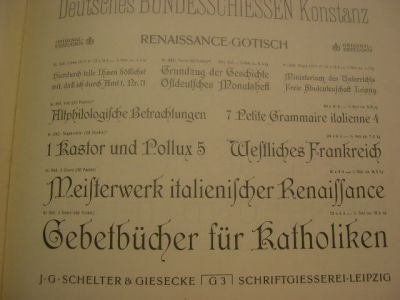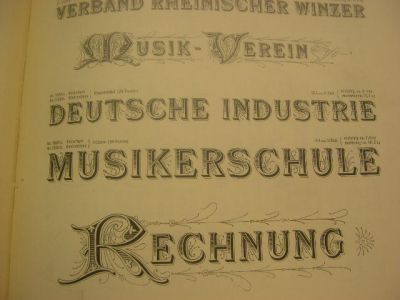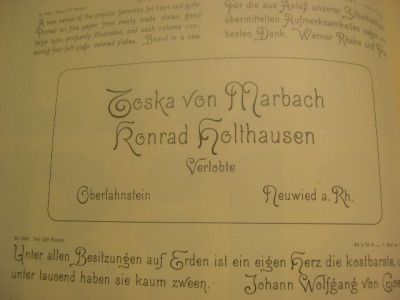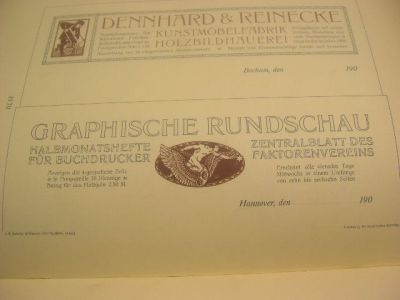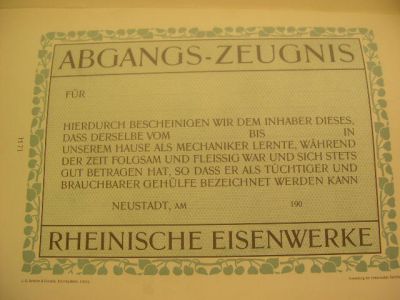
Gott grüß die Kunst.
Das möchte ich als Bleisetzer Euch digitalen Typographen zurufen und damit auch gleich feststellen, daß ich, als Mann der Bleisatz-Zeit, Eure Arbeit durchaus schätze. Darüber hinaus sehe ich sinnvolle Möglichkeiten, Euch bei Eurer Arbeit zu unterstützen.
Seit ca. einem Jahre drucke ich an meiner Schriftensammlung des Preußischen Bleisatz-Magazin. Die erste Ausgabe, hergestellt im Buchdruck in einer Mini-Auflage, wird zu Ostern 2006 fertig sein und wird 200 Schriftmuster von Bleisatz-Schriften beinhalten, deren Erstguß zwischen 1895 und 1976 liegt.
Danach teilt sich das Projekt:
- Zum einen drucke ich weitere Schriften, denn ich habe noch eine ganze Reihe schöner Bleisatz-Schriften und bekomme immer wieder welche, die ich noch nicht gedruckt habe.
- Zum anderen wird die Buchdruck-Ausgabe Grundlage für eine Print-Ausgabe im Offsetdruck, deren Erscheinen für Dezember 2006 geplant ist.
Anlaß, mich hier zu registrieren, war ein Zufall. Ich recherchierte über die Ehmcke-Antiqua, fand einen Diskussions-Strang in diesem Forum und bin mit einigen der Ansichten dort nicht konform. Dazu möchte ich (dort) etwas schreiben.
Also mein Angebot steht:
Schaut Euch doch einmal meine Schriftensammlung an:
hallo bleisetzer,
ist das schelter und giesecke specimen, das du mir vor der nase weggeschnappt hast, schon bei dir angekommen? kannst du mal ein paar bilder posten.
hallo bleisetzer,
ist das schelter und giesecke specimen, das du mir vor der nase weggeschnappt hast, schon bei dir angekommen? kannst du mal ein paar bilder posten.
ja, das ist die Hauptprobe von Schelter & Giesecke, Leipzig.
Sie stammt aus dem Jahr 1908 und ist sehr selten.
Letterpress Specimen aus England oder den VSvA sammle ich nicht. Kenne sie zwar, aber ich liebe die deutschen Schriften. Am liebsten aus der Zeit 1900 bis 1940.
Bei solche Hauptproben kann ich nicht an mir halten.
Es sind rd. 1.000 Seiten, das Buch wiegt 3,5 kg.
"Ein paar Bilder posten" ist schwierig. Welche von den 1.000 Seiten?
Gott grüß die Kunst
Bei solche Hauptproben kann ich nicht an mir halten.
Es sind rd. 1.000 Seiten, das Buch wiegt 3,5 kg.
"Ein paar Bilder posten" ist schwierig. Welche von den 1.000 Seiten?
da dieses ding schon lage auf meiner wunschliste steht, würde ich mich umsomehr über ein paar bilder vom inhalt freuen. such dir doch die schönsten 10 seiten aus und fotografier sie.
Bei solche Hauptproben kann ich nicht an mir halten.
Es sind rd. 1.000 Seiten, das Buch wiegt 3,5 kg.
"Ein paar Bilder posten" ist schwierig. Welche von den 1.000 Seiten?
da dieses ding schon lage auf meiner wunschliste steht, würde ich mich umsomehr über ein paar bilder vom inhalt freuen. such dir doch die schönsten 10 seiten aus und fotografier sie.
Nun gut. Aber nicht ganz kommentarlos:
Die Hauptprobe von Schelter & Giesecke fällt in die Jugendstil-Zeit. Das Unternehmen war einer der Marktführer für Bleisatz-Schriften, Ornamente und Verzierungen sowie Messing-Produkte (die für Prägungen benötigt wurden).
Die Hauptprobe stammt aus dem Jahr 1908. In dieser Zeit, also vor dem I.Weltkrieg, wurden Schriften geschaffen wie:
Eckmann (1900):
Billet (1911):
Kleopatra (1912):
Man muß Schriften aus ihrer eigenen Zeit heraus sehen. Dann erschließt sich der Zusammenhang mit der geschichtlichen Epoche. Das ist etwas, was die DIN 16 518, nach der alle meine Schriften klassifiziert sind, nicht wiedergibt. Weshalb diese Art der Klassifizierung auch von vielen Bleisatz-Freunden abgelehnt wird. Die klassifizieren nach Epochen.
Hoffmanns Schriftatlas
Herausgegeben von Alfred Finsterer.